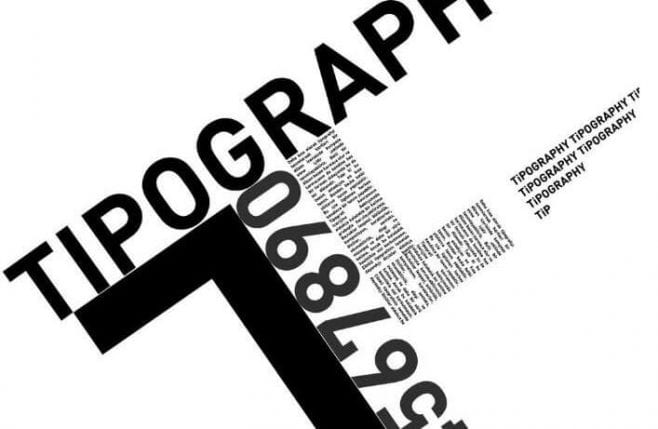
9 consejos para una mejor tipografía
El texto es parte fundamental de una página web, no solo aportando información sino que además forma parte del diseño de la página.
¿Sabías que el texto es una parte fundamental de tu página web? Éste no solo aporta información, sino que además forma parte del diseño de tu página
En esta oportunidad han enumerado 9 consejos para una mejor tipografía al alcance de los usuarios:
1- Nunca combines 2 fuentes similares
2- Una menos fuentes para mantener la armonía
3- Crea una jerarquía fuerte para transmitir los mensajes
4- Combinar los tipos de letra con los estados de ánimo complementarios.
5- Tener cuidado con Kening & Tracking
6- Evitar fuentes incorrectas
7- El contraste es la clave
8- Nunca estirar una fuente
9- Salir de su zona de confort helvética